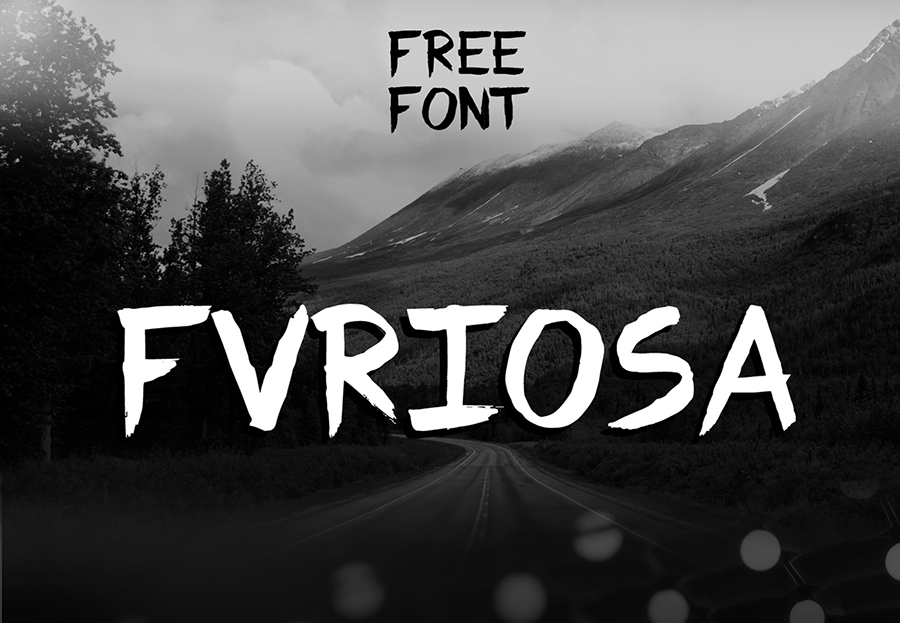
Fvriosa Font – Download Grátis
A Fvriosa é uma fonte script autêntica e criativa feita com paixão por Fausto Furioso. Essa fonte perfeita para uso em anúncios, headlines, rótulos, tags e painéis de propaganda. Para explorar ainda mais o trabalho do designer, visite seu portfólio. A Fvriosa é um ativo valioso para designers que buscam uma fonte única para seus projetos gráficos. Se você está procurando por algo elegante e autêntico, certamente esta font vai deixá-lo impressionado.